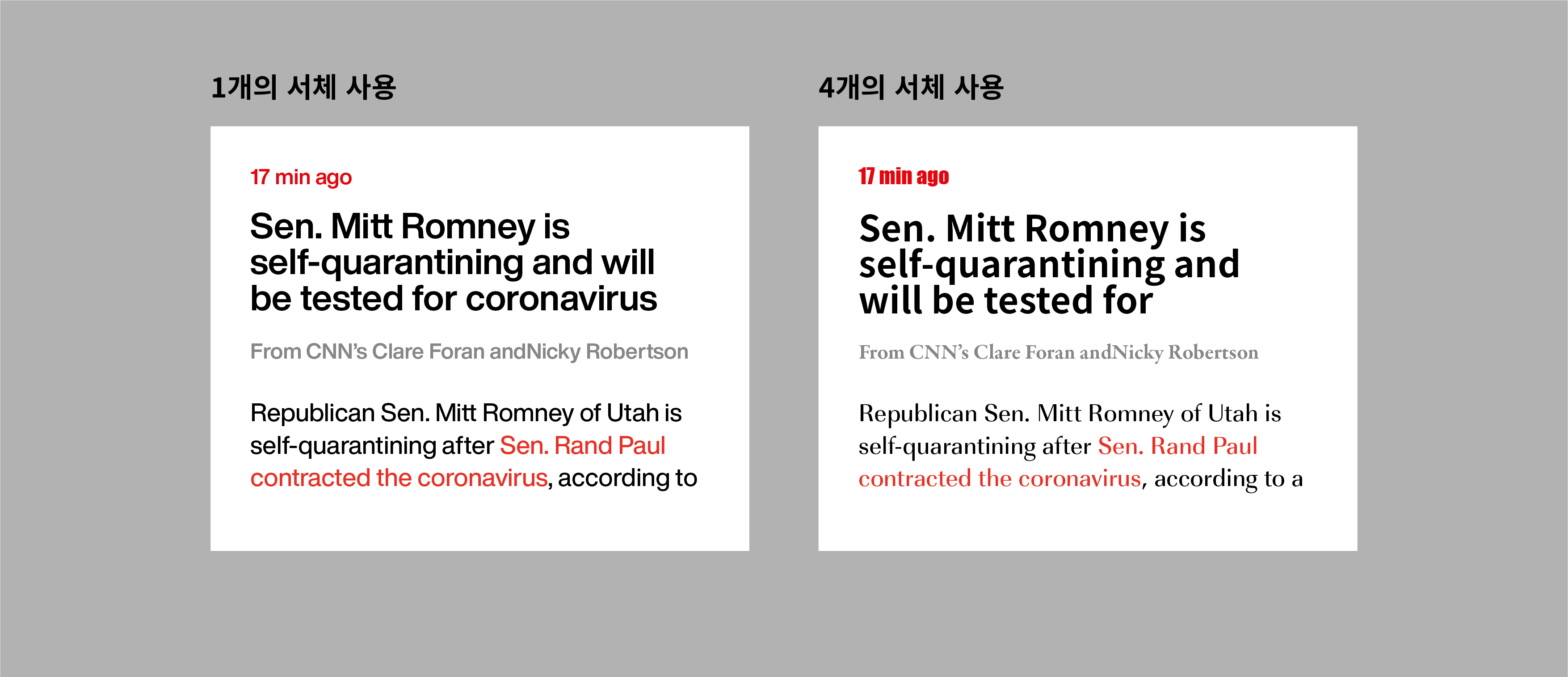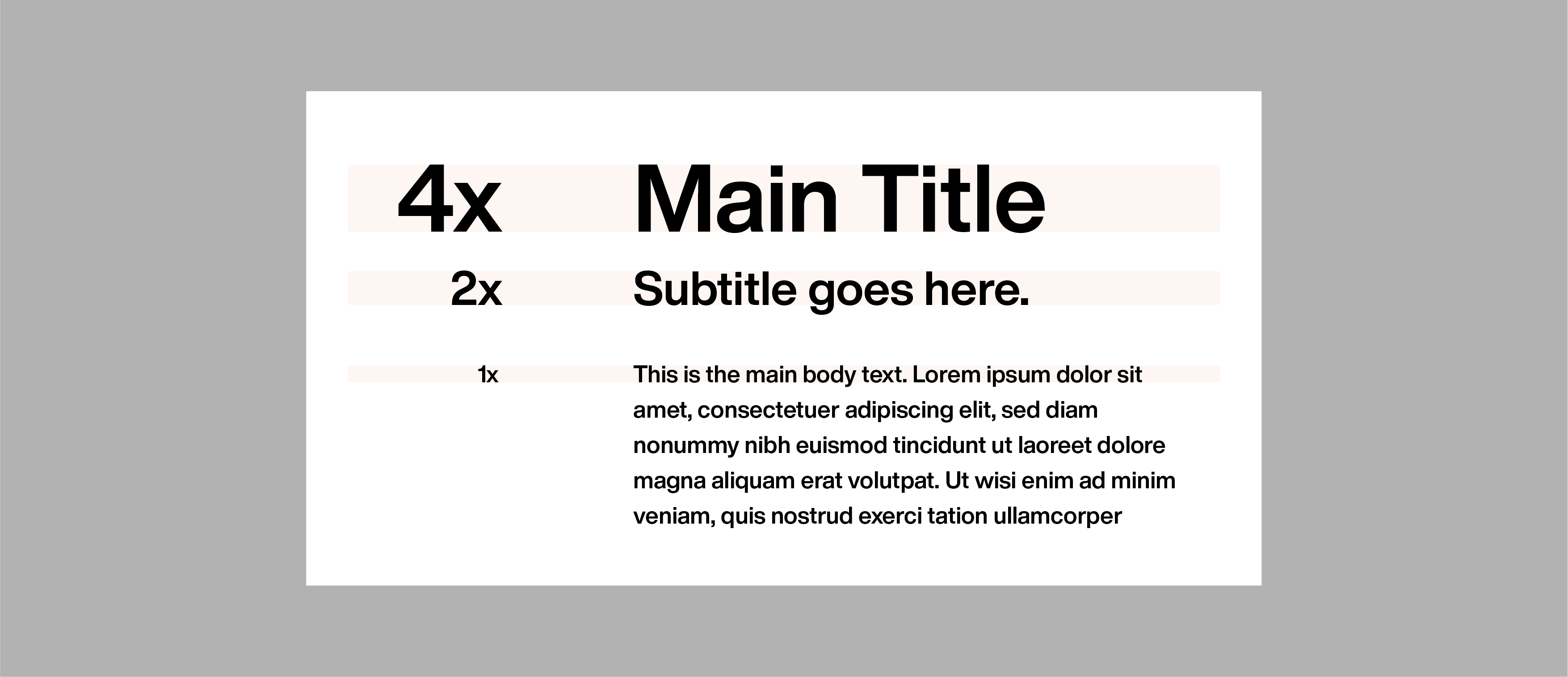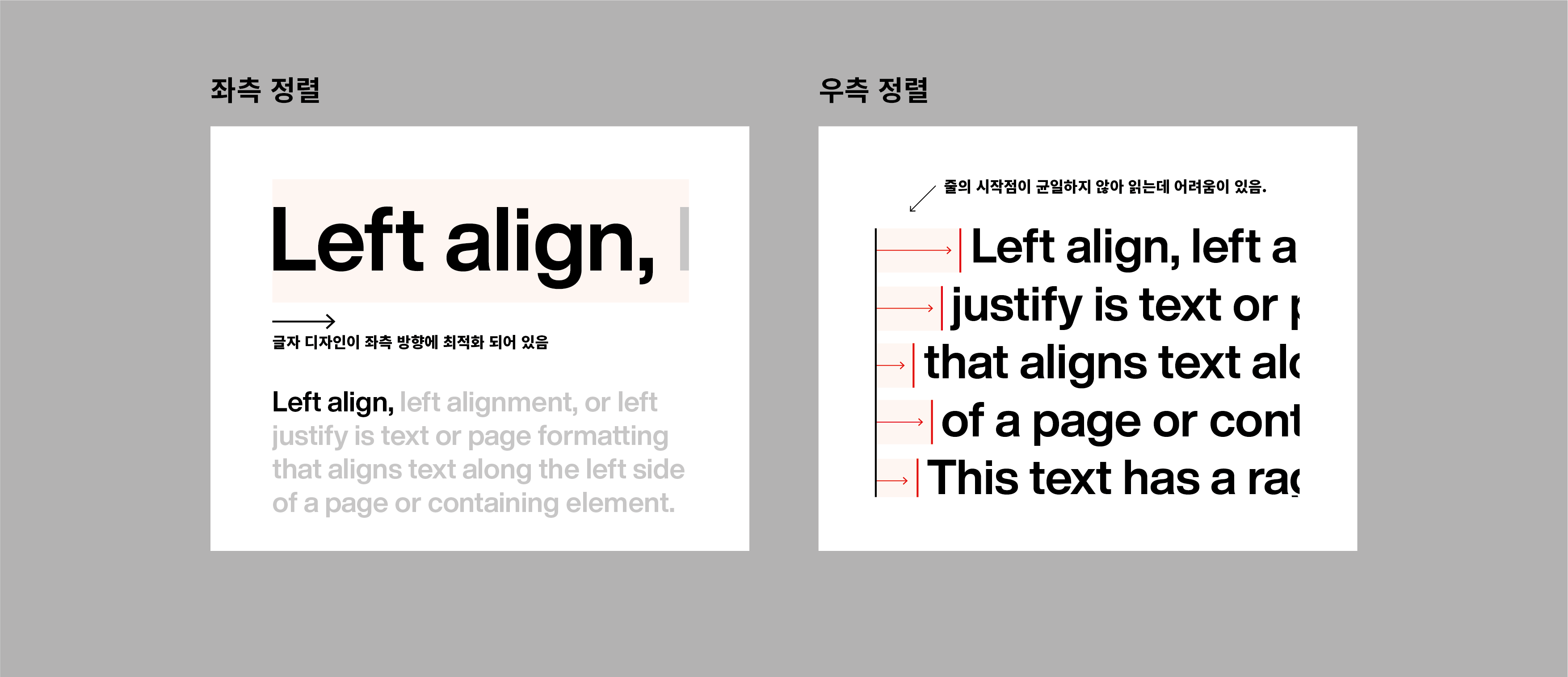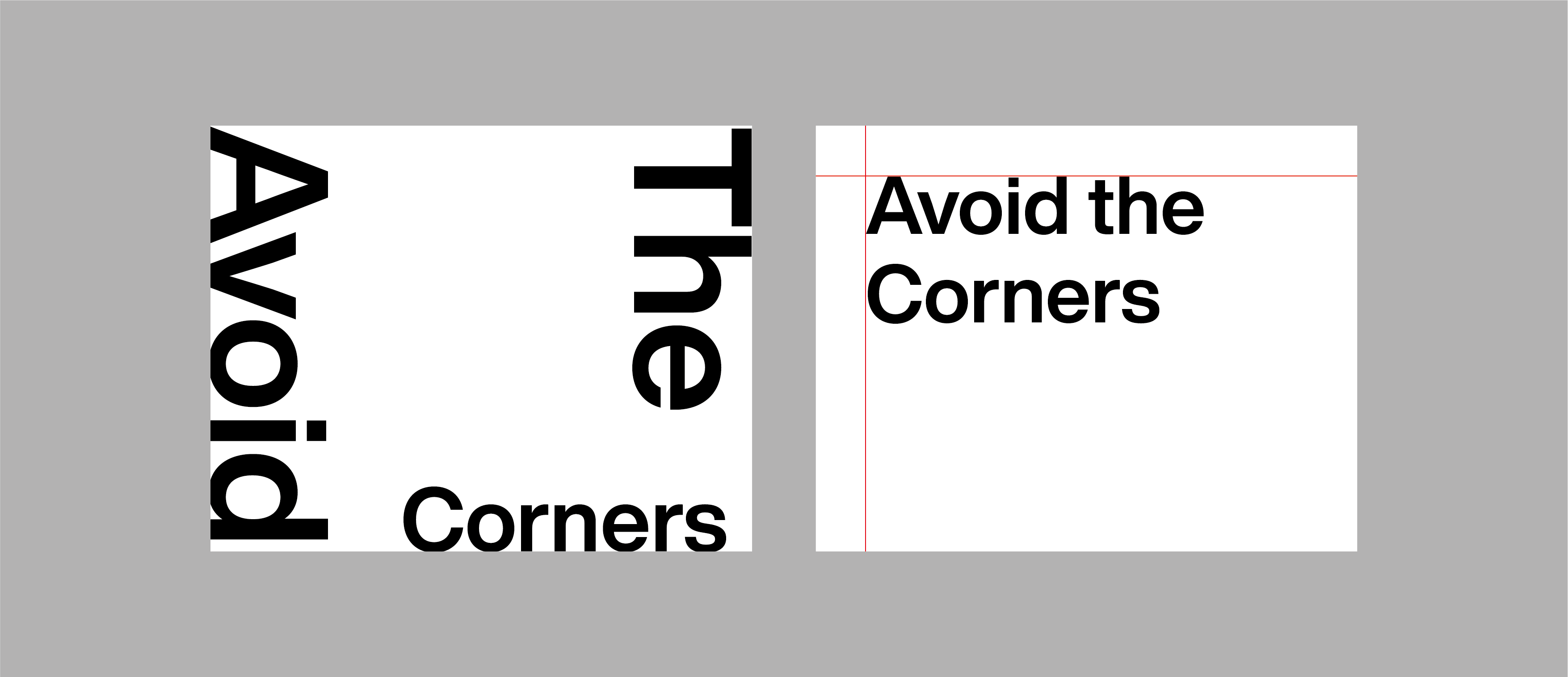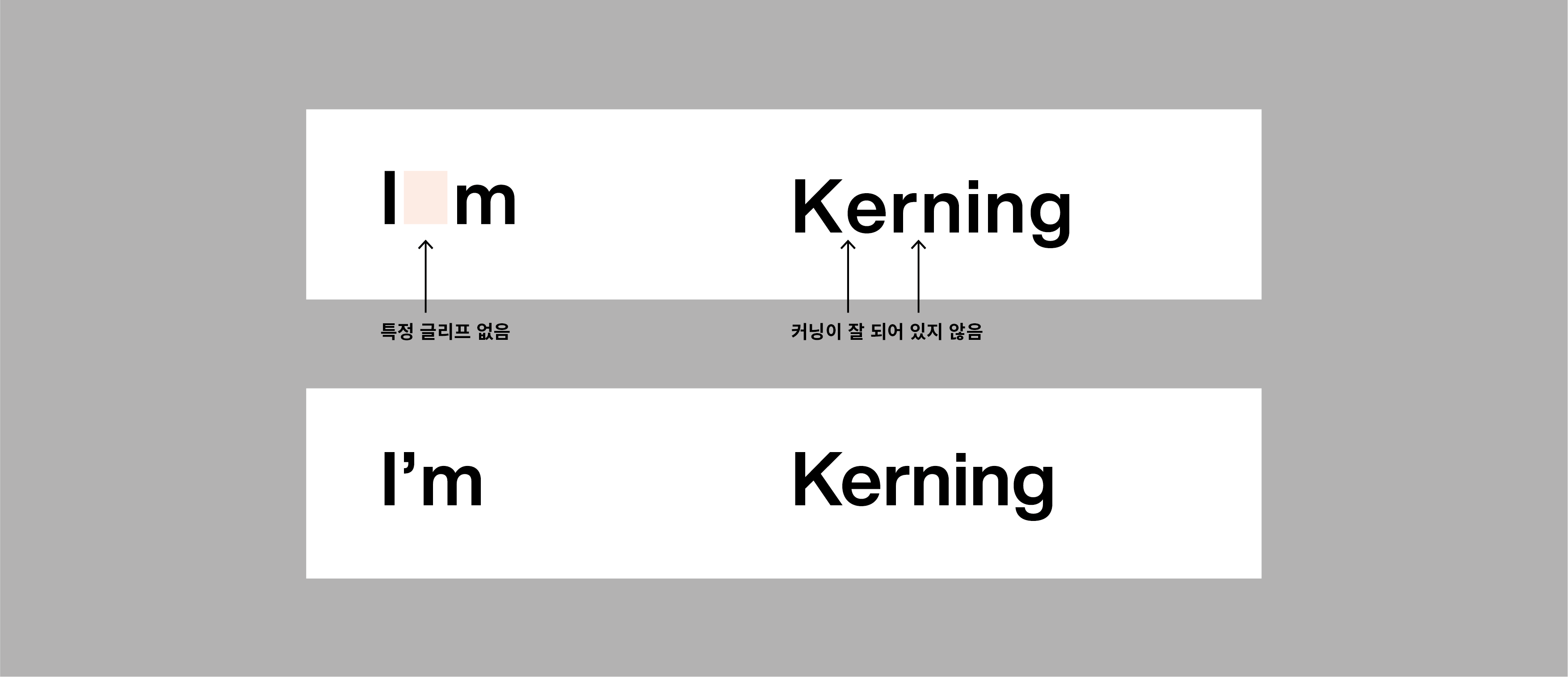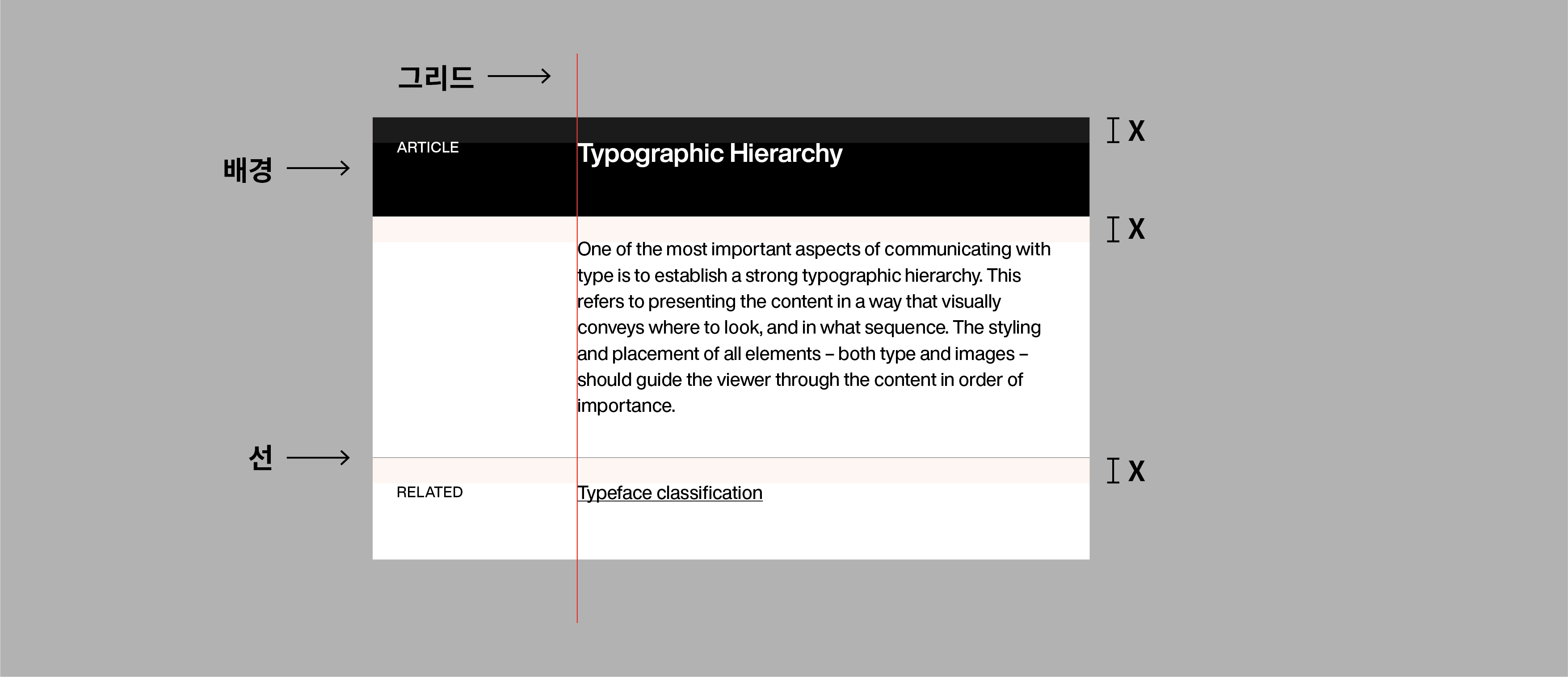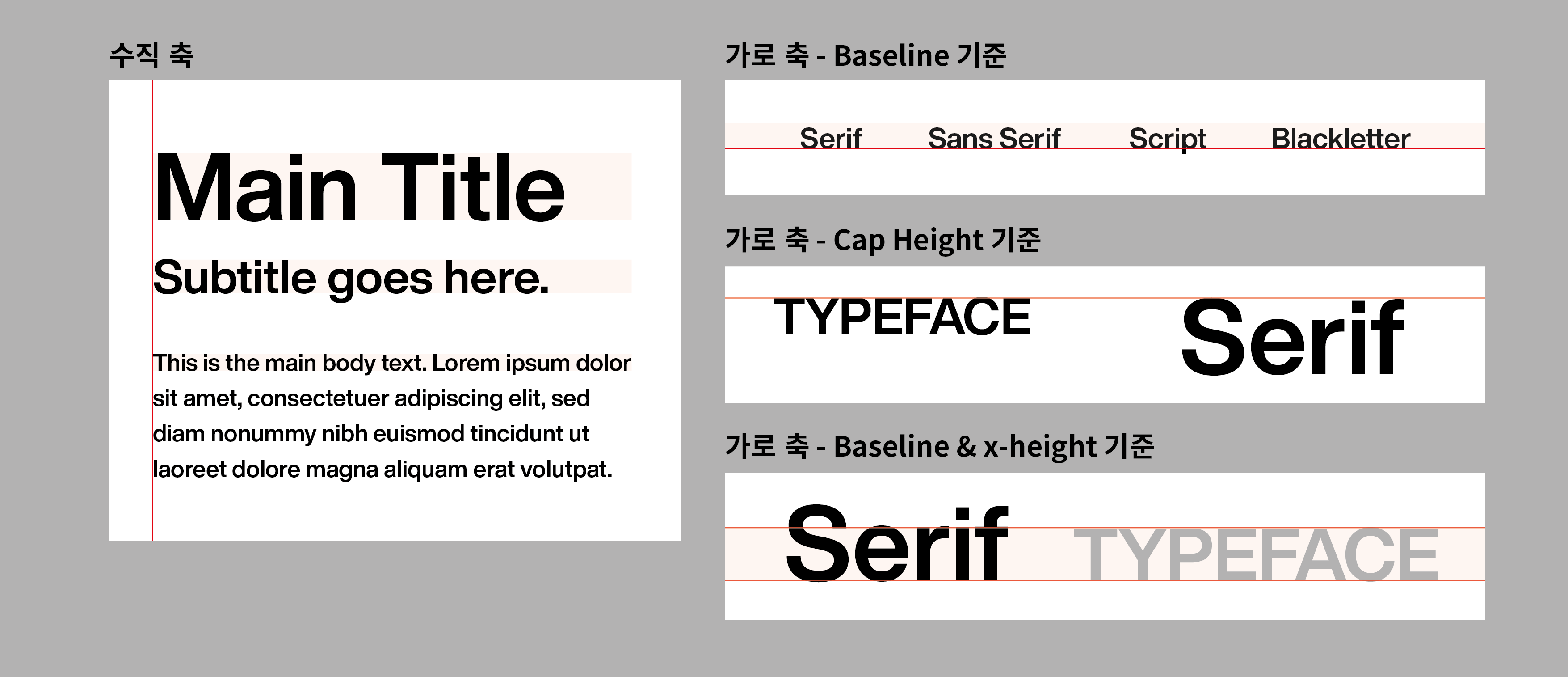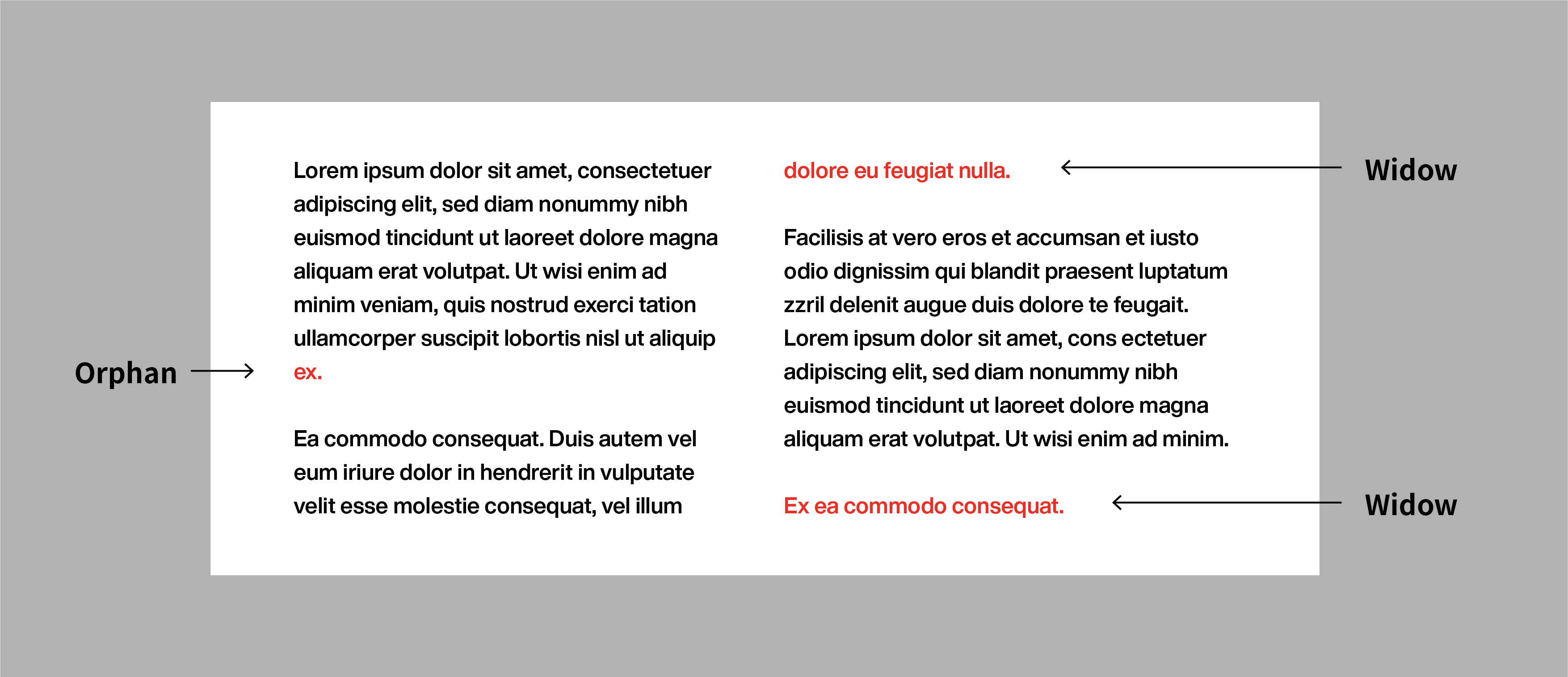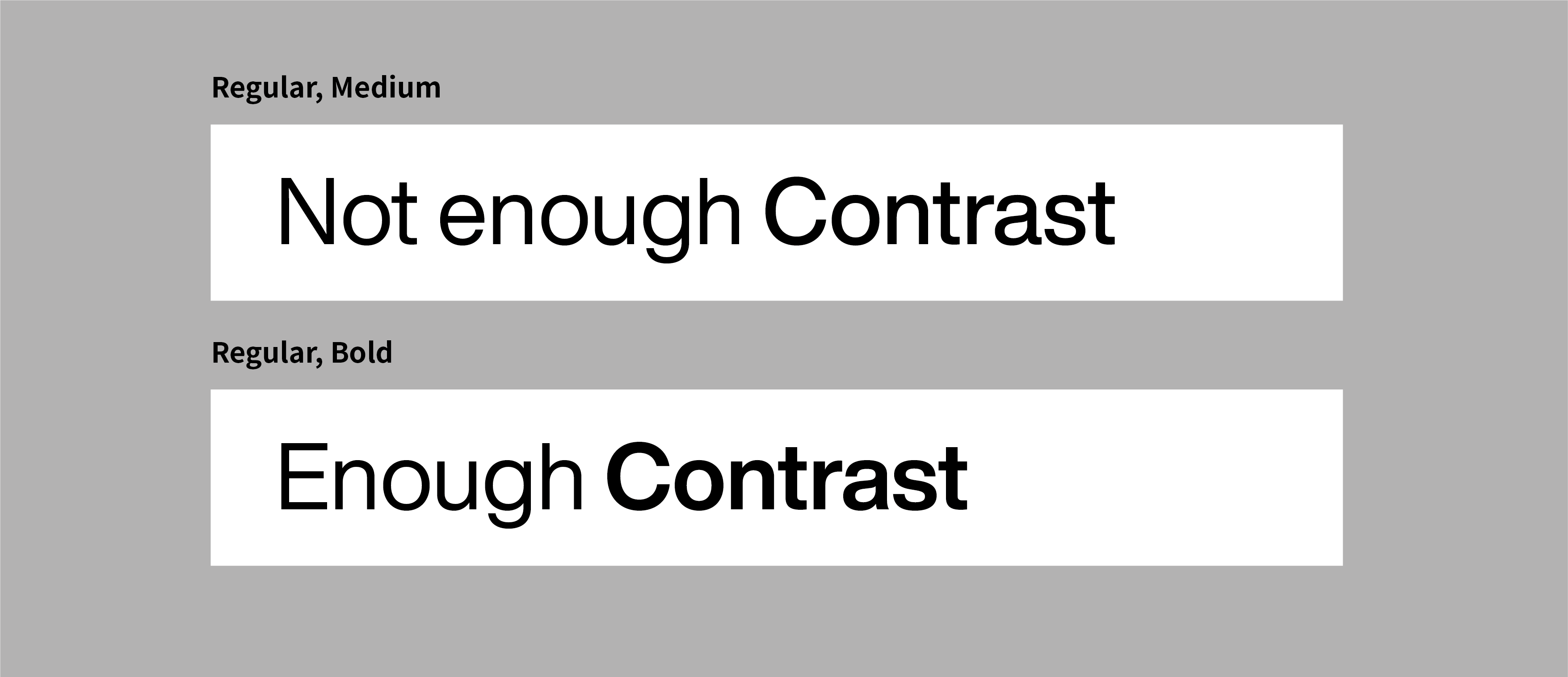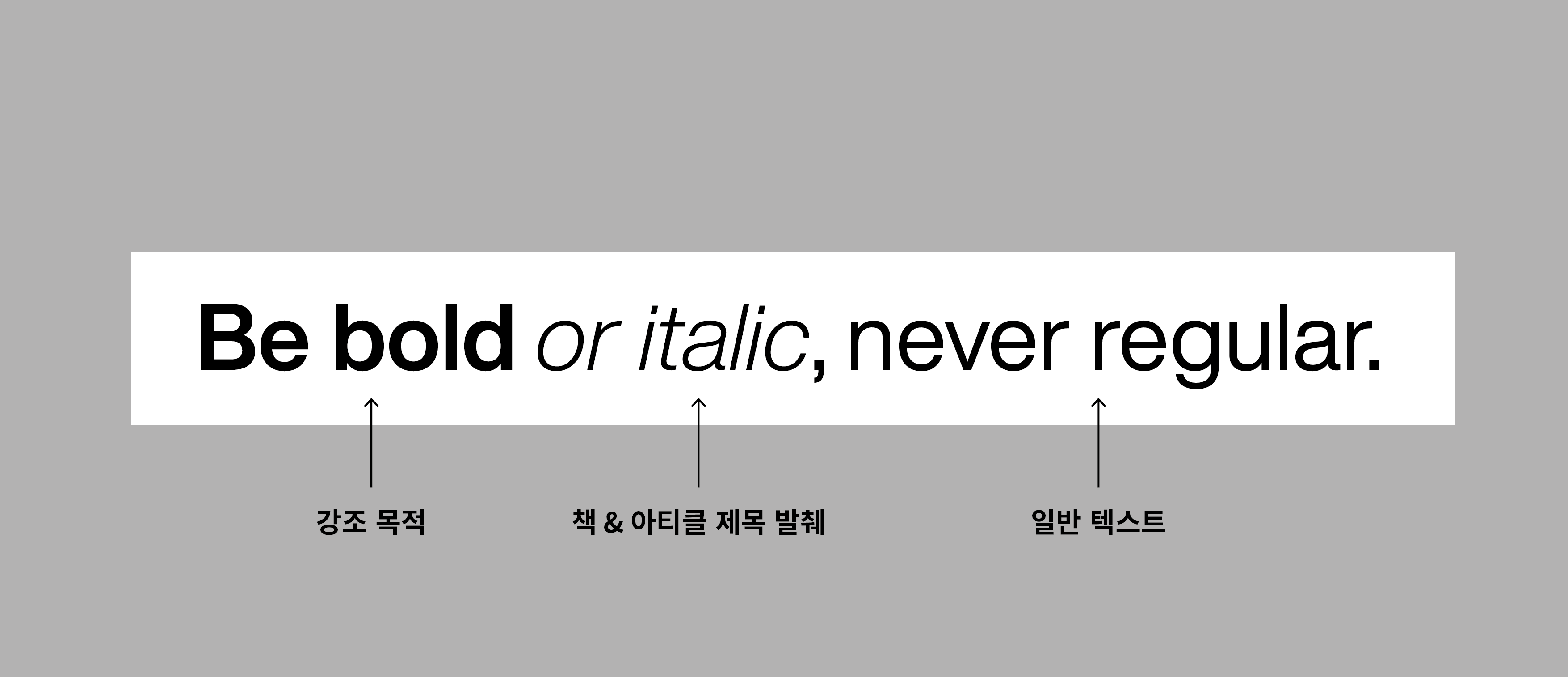
좋은 타이포그래피를 위한 10가지 Tip
Typography Manual for Graphic Design
본글은 유명 디자인 채널인 The Futur에서 제작한 Typography Manual이라는 영상을 기반하였으나 제 경험과 지식을 토대로 부족한 설명을 추가하거나 수정하였습니다.
1. 좌측 정렬하기
영문은 정말 특별한 경우가 아니라면 좌측 정렬(left-aligned)을 최우선으로 합니다. 이는 영문 자체가 왼쪽에서 오른쪽 방향으로 읽게 디자인되어 있기 때문입니다. 특히 문단일 경우 한 줄에서 다음 줄로 넘어갈 시에 시선이 빠르게 따라가지 못하여 읽는 속도가 더뎌질 수 있습니다.
2. 하나의 서체(Typeface) 사용하기
하나의 글꼴(혹은 폰트 family)에는 다양한 용도에 맞는 폰트들이 있고 이들만으로 일관적이고 체계적인 디자인이 가능합니다. 특별한 의도 없이 한 디자인에 여러 서체를 남용하지 마세요.
3. 폰트 두께 스킵하기
한 서체 내에서 여러 두께의 폰트를 사용할 경우, 명확한 대비를 위해 폰트의 두께 차이가 한 개 이상 차이나야 합니다. 예를 들어 본문용으로 Regular를 사용하신다면 타이틀은 다음 두께(Medium)가 아닌 Bold를 사용하셔야 합니다.
4. 글자 크기 x 2
폰트의 위계를 세울 때 글자의 크기를 2배 단위로 하면 손쉽게 텍스트 사이의 대비를 이룰 수 있습니다. 더 큰 대비를 위해서는 3배, 혹은 4배까지 할 수 있습니다.
5. 한 축에 정렬하기
텍스트 요소들을 한 축에 기준해서 정렬하세요. 세로축에 기준할 경우 글자의 왼쪽에 맞추며, 가로축을 기준으로 할 경우 Baseline 혹은 Cap Height를 기준으로 정렬하시는 게 좋습니다.
세로축
- 왼쪽에 기준. (오른쪽 정렬 시에는 텍스트를 All Caps으로 세팅하기)
가로축
- Baseline 기준
- Cap Height 기준
- 큰 텍스트의 Baseline과 x-Height를 기준(이 경우 작은 텍스트는 전부 대문자로 설정)
6. 룰을 사용하여 그룹화하기
연관된 정보들을 선, 간격, 배경색과 같은 규칙을 세워 그룹화하세요. 서로 다른 요소들을 시각적으로 정리할 수 있습니다.
7. 검증된 폰트 사용하기
시스템 폰트 혹은 브랜딩을 위해서 서체를 정할 때 필요한데 빠진 글리프는 없는지, 혹은 잘못된 커닝은 없는지 샘플 텍스트를 사용하여 확인하세요. 프로젝트의 시간과 비용을 아낄 수 있습니다.
8. 모서리 피하기
텍스트를 정교하게 자르는 것이 아니라면 텍스트를 모서리에 배열하는 것을 되도록 피하세요. 여백은 텍스트가 숨 쉴 공간을 주기 위해 필요합니다.
9. 간격 유의하기
타이포그래피는 얼마나 간격을 잘 조정하는지가 전부입니다. 단순히 공간을 채우기 위해 양쪽 정렬을 하지 마세요. 하이픈(-)을 적절히 사용하는 것도 방법입니다.
다중 칼럼을 사용할 경우에는 단어가 문단 끝에 홀로 남거나(orphan), 다음 칼럼으로 한 줄만 남는 경우를 피하세요(widow). 글의 이해도를 방해할 수 있습니다.
10. 용도에 맞는 폰트 사용하기
용도에 적절한 폰트를 사용하세요. 볼드체는 특정 단어를 강조하거나 이탤릭체는 책 혹은 기사 제목을 인용할 때 사용됩니다. 이런 폰트 사용법은 사용자가 글의 정보를 빠르고 명확하게 파악하는데 도움이 됩니다.